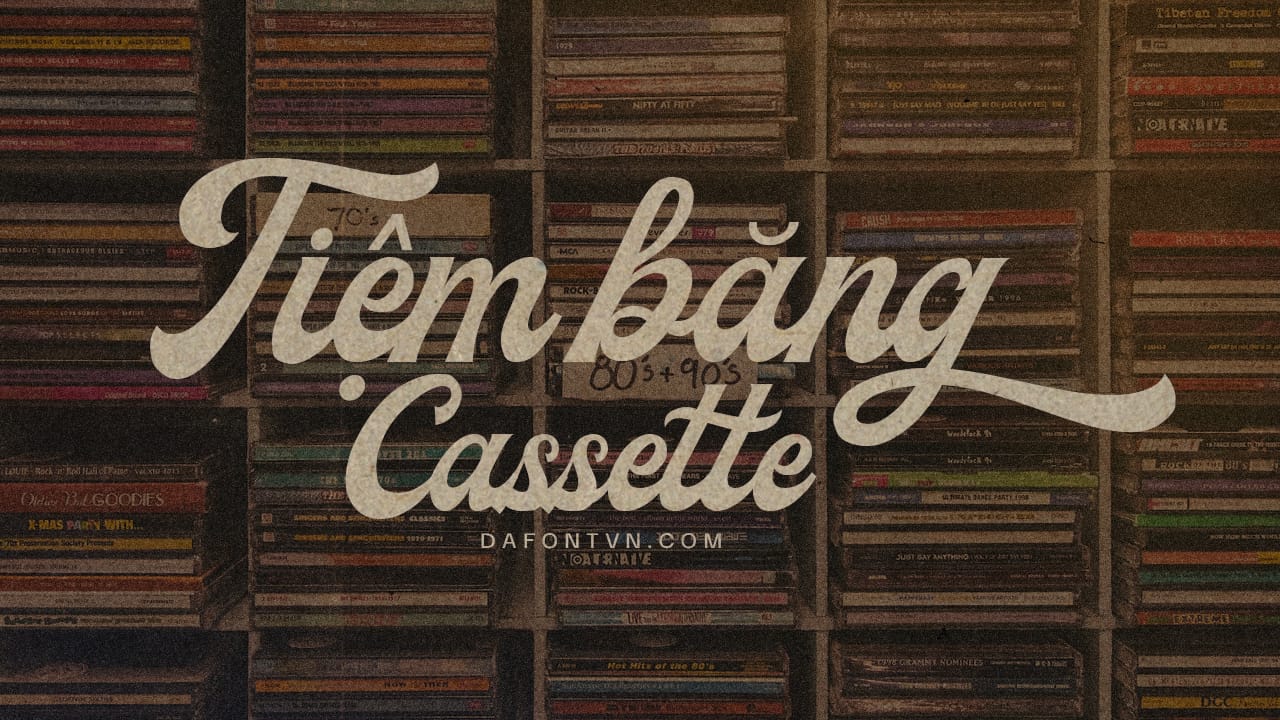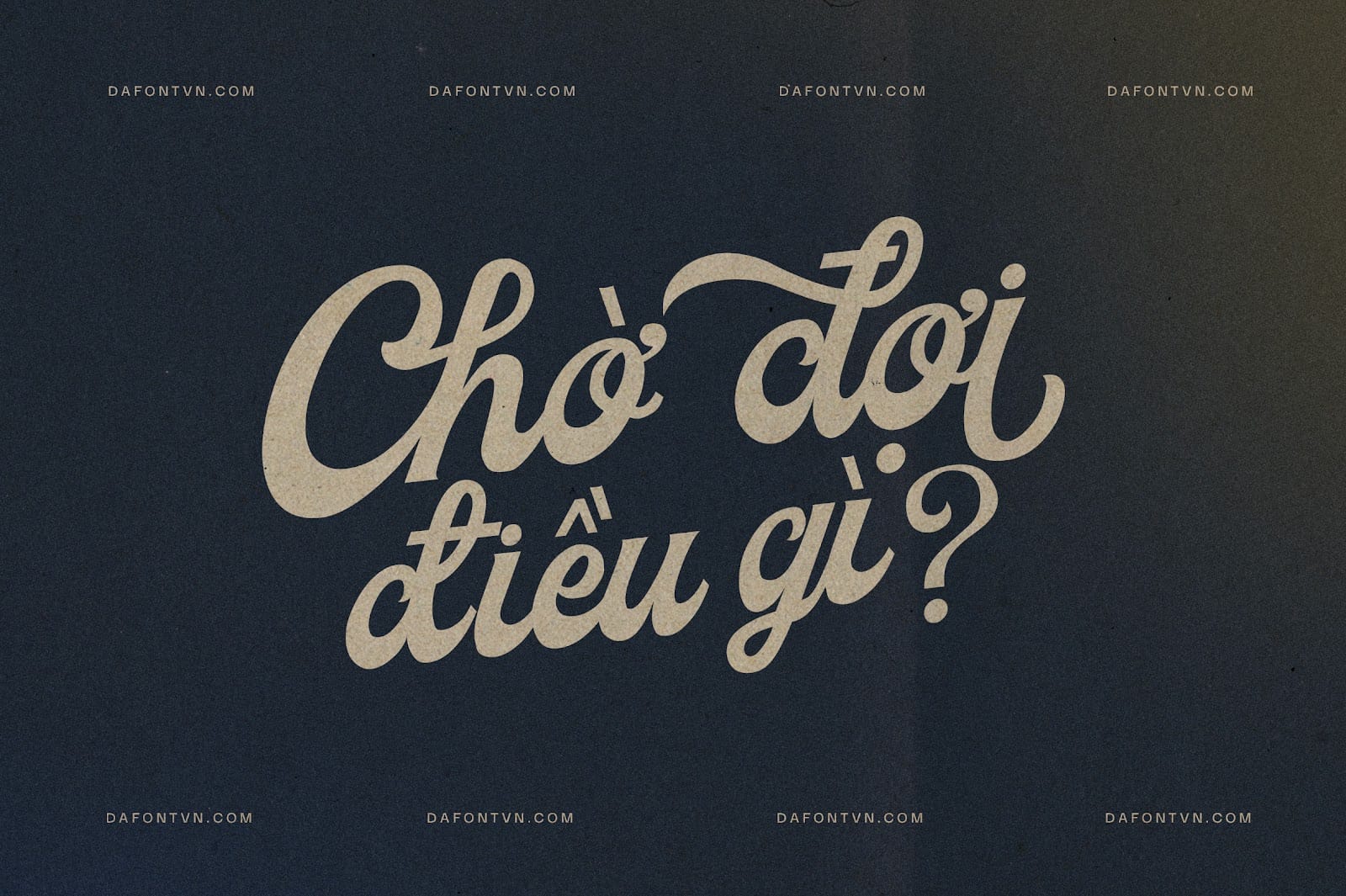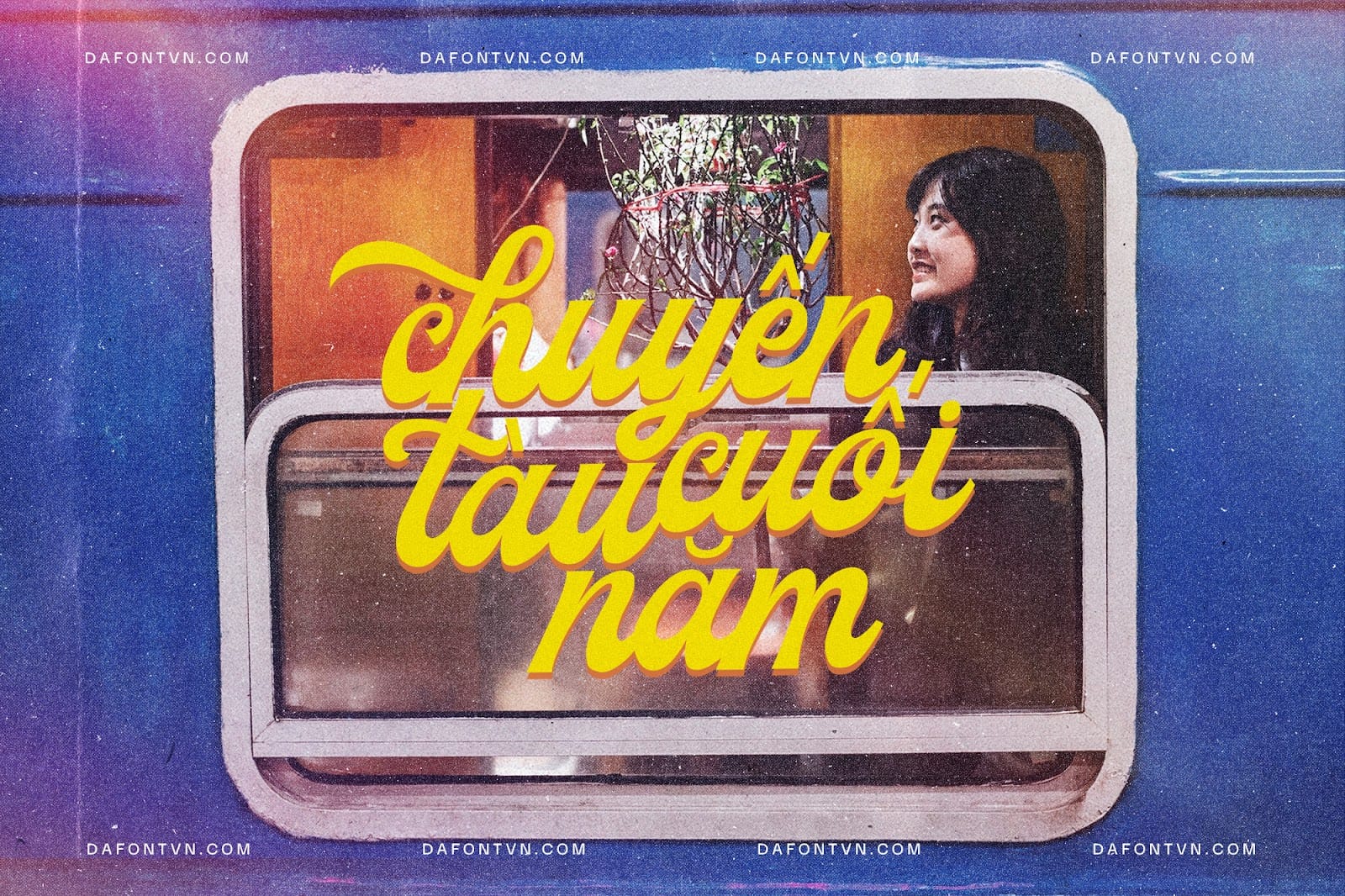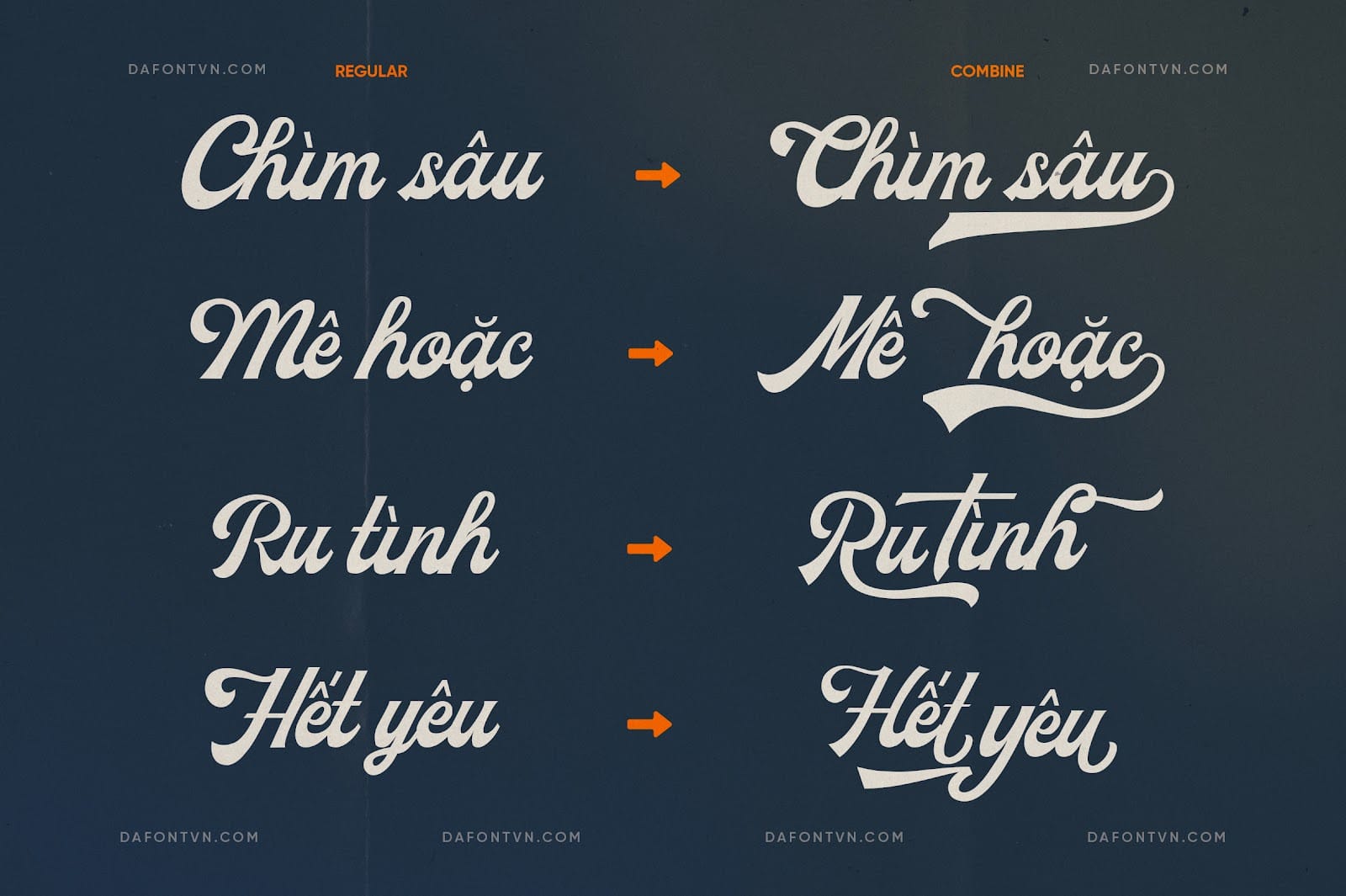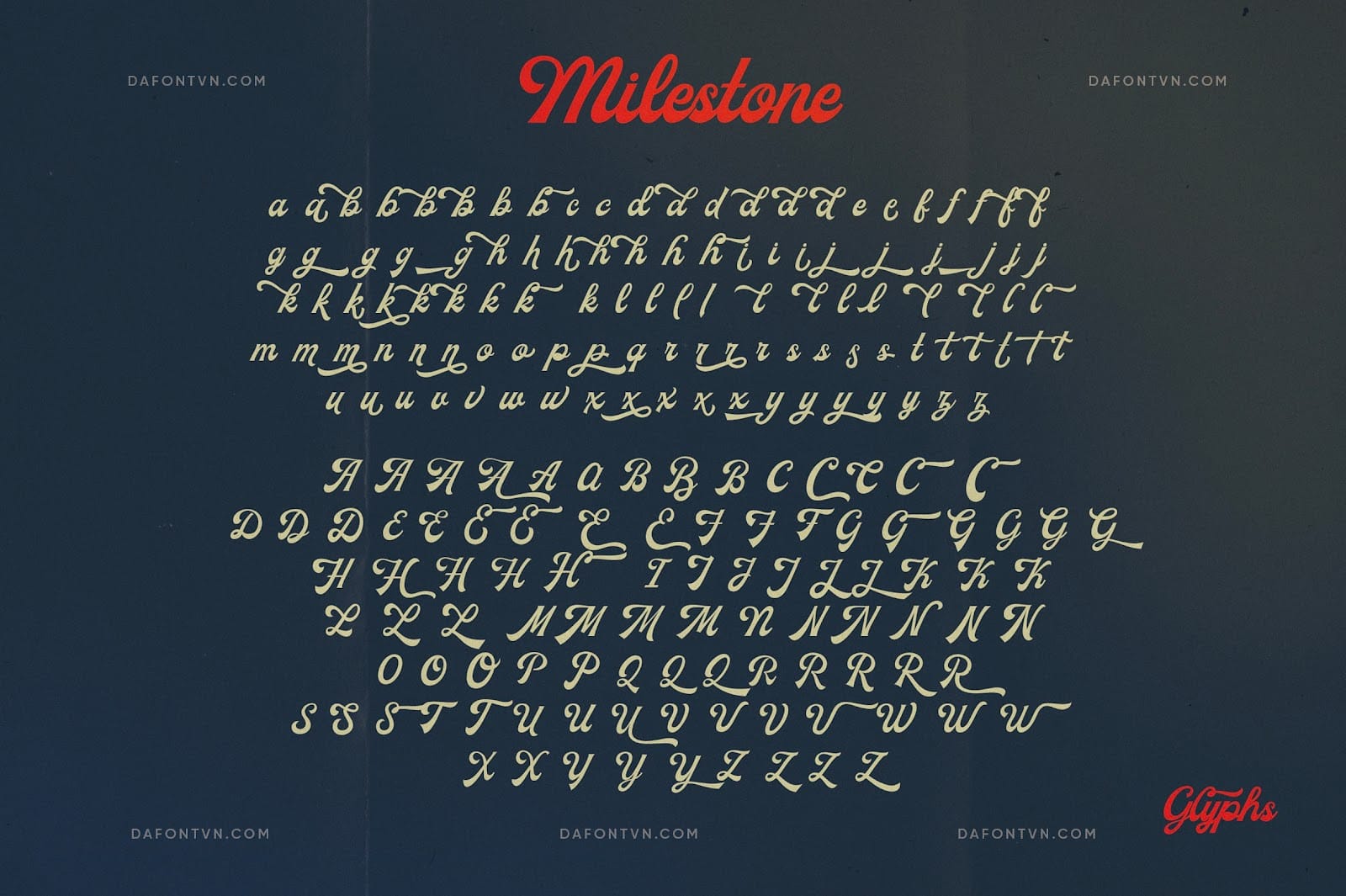
Font Milestone Script Việt hóa – Font chữ cổ điển
Giới thiệu font Milestone Script, một kiểu chữ cổ điển tinh tế và thanh lịch lấy cảm hứng từ môn thể thao bóng chày, phông chữ này là sự pha trộn hoàn hảo giữa phong cách cổ điển và chữ viết tay, được tạo ra với sự tỉ mỉ đến từng chi tiết và nét cá nhân hóa cho từng đường cong.
Phông chữ Milestone Script Việt hóa là một phông chữ linh hoạt có thể được sử dụng trong nhiều dự án khác nhau như vẽ ký hiệu, nhãn dán, phù hợp làm logo, bao bì, sản phẩm, nhãn mác, quán cà phê kiểu xưa cũ, quán bar và mọi thứ mang nét đặc trưng của thời xưa.
Với tính thẩm mỹ lấy cảm hứng từ cổ điển và hoài cổ của nó mang đến cảm giác vượt thời gian và hoài cổ, khiến font Milestone trở thành một lựa chọn tuyệt vời để gợi lên cảm giác hoài cổ hoặc sự hấp dẫn cổ điển.